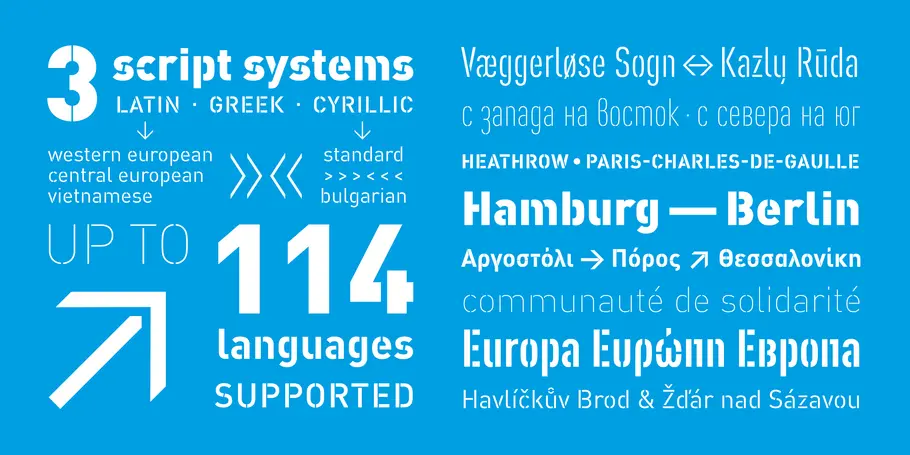
FF DIN Stencil.
Más FF DIN que nunca.
FF DIN Stencil está impregnada del ADN único de su familia. Y, aunque abre un nuevo mundo de posibilidades gracias a sus características únicas, es fiel a la filosofía del diseño de FF DIN, basada en la precisión de la ingeniería. La familia FF DIN tiene un halo de versatilidad y autoridad, y FF DIN Stencil sigue los mismos principios de diseño, pero con un toque extra de estilo.
FF DIN: la famosa, fiel y primera reedición de DIN 1451. FF DIN tiene su origen en los modelos de letras del estándar alemán DIN 1451 y se considera la tipografía estándar perfecta debido a su diseño metódico y especializado.
La familia FF DIN tiene un halo de versatilidad y autoridad, y FF DIN Stencil sigue los mismos principios de diseño, pero con un toque extra de estilo. Los puentes de las letras son verticales y suelen reemplazar las partes más finas de los trazos, lo que da profundidad a los títulos.
Aumenta el tamaño del texto para reforzar tus afirmaciones: a medida que el peso aumenta, la anchura de los puentes crece o mengua para que FF DIN Stencil siga siendo eficaz, sean cuales sean el volumen y el estilo elegidos.
También está disponible como fuente variable para que se puedan diseñar variaciones muy específicas que queden bien en cualquier espacio de diseño y logren animar así el movimiento de un estado al siguiente. Abraza la innovación con toda la familia FF DIN: el espaciado y el kerning de FF DIN Stencil son idénticos a los de FF DIN, por lo que puedes hacer los intercambios que quieras con cualquier fuente FF DIN sin modificar la longitud de las palabras ni los saltos de línea.
FF DIN Slab y FF DIN Stencil, diseñados por Albert-Jan Pool, Antonia Cornelius y Achaz Reuss, pueden ser complementos idóneos para la familia FF DIN para quienes sienten devoción por ella. Todas las extensiones de FF DIN están impregnadas del ADN único de su familia. Y, aunque abren un nuevo mundo de posibilidades gracias a sus características únicas, son fieles a la filosofía del diseño de FF DIN, basada en la precisión.
Albert-Jan Pool nació en Ámsterdam el 9 de julio de 1960. Tras estudiar en la Royal Academy of Arts (KABK) de La Haya con Gerrit Noordzij, se marchó a Hamburgo en 1987 y trabajó con Scangraphic y URW. Desde 1994, lleva su propio estudio, Dutch Design, y diseña tipografías, como FF OCR y FF DIN, así como tipos de letras corporativas para Jet/Conoco, C&A y HEM/Tamoil.
Antonia Cornelius es una diseñadora de tipografía y comunicación, docente, autora e investigadora alemana con especial interés en la legibilidad y la fluidez. Estudió diseño de la comunicación centrado en el diseño tipográfico con Jovica Veljović en la Universidad de Ciencias Aplicadas de Hamburgo. Justo después de terminar su máster, Antonia se unió a Dutch Design para ampliar la familia FF DIN con FF DIN Slab. Además, se dedicó incansablemente a diseñar el contorno de FF DIN y FF DIN Stencil para convertirlas en fuentes variables.
Achaz Reuss se graduó como diseñador de comunicación en la Universidad de Ciencias Aplicadas de Hamburgo en 1983. Trabajó como diseñador tipográfico en URW y fundó su propia agencia de diseño, Reuss Design, en 1995, especializada en diseño y tipografía corporativos. Diseñó los tipos de letras de marca de NIVEA y Milram. FontShop publicó su familia tipográfica FF Qtype en 2004. En 1995, trabajó en los cinco primeros pesos de la tipografía FF DIN de Albert-Jan Pool y diseñó FF DIN Stencil, que se lanzó en 2022.